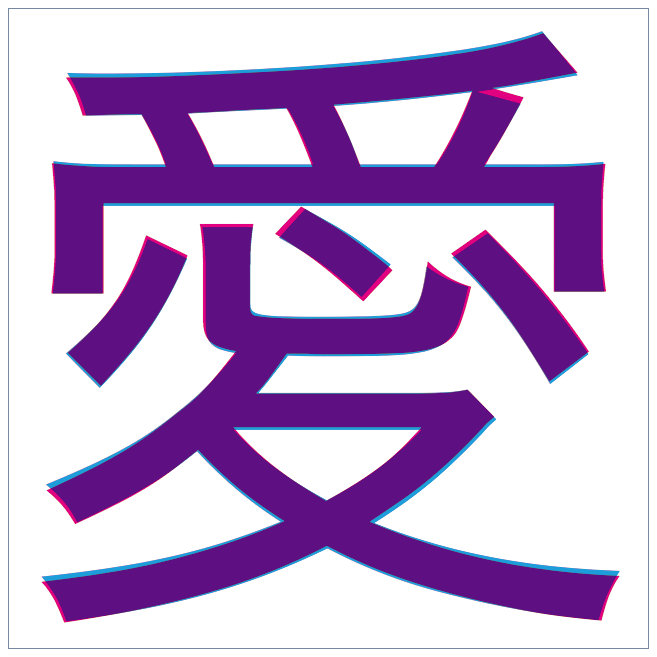
LionのAquaKanaは太くて細くて長い
- LionのAquaKanaは漢字が太くなったという話(http://blog.coluli.net/「LionのAquaKana」)。ウエイト的にはヒラギノ角ゴW4に近いが、それとも微妙に違うらしい。ということで、もちろん重ねてみた。下図、赤がLionのAquaKana、青がヒラギノ角ゴW4。
- この1字だけを見て言うのもアレだが、LionのAquaKanaの漢字は、ヒラギノ角ゴと比べて縦画が太く、横画が細く、各パーツがちょっと長い、というかんじだろうか。